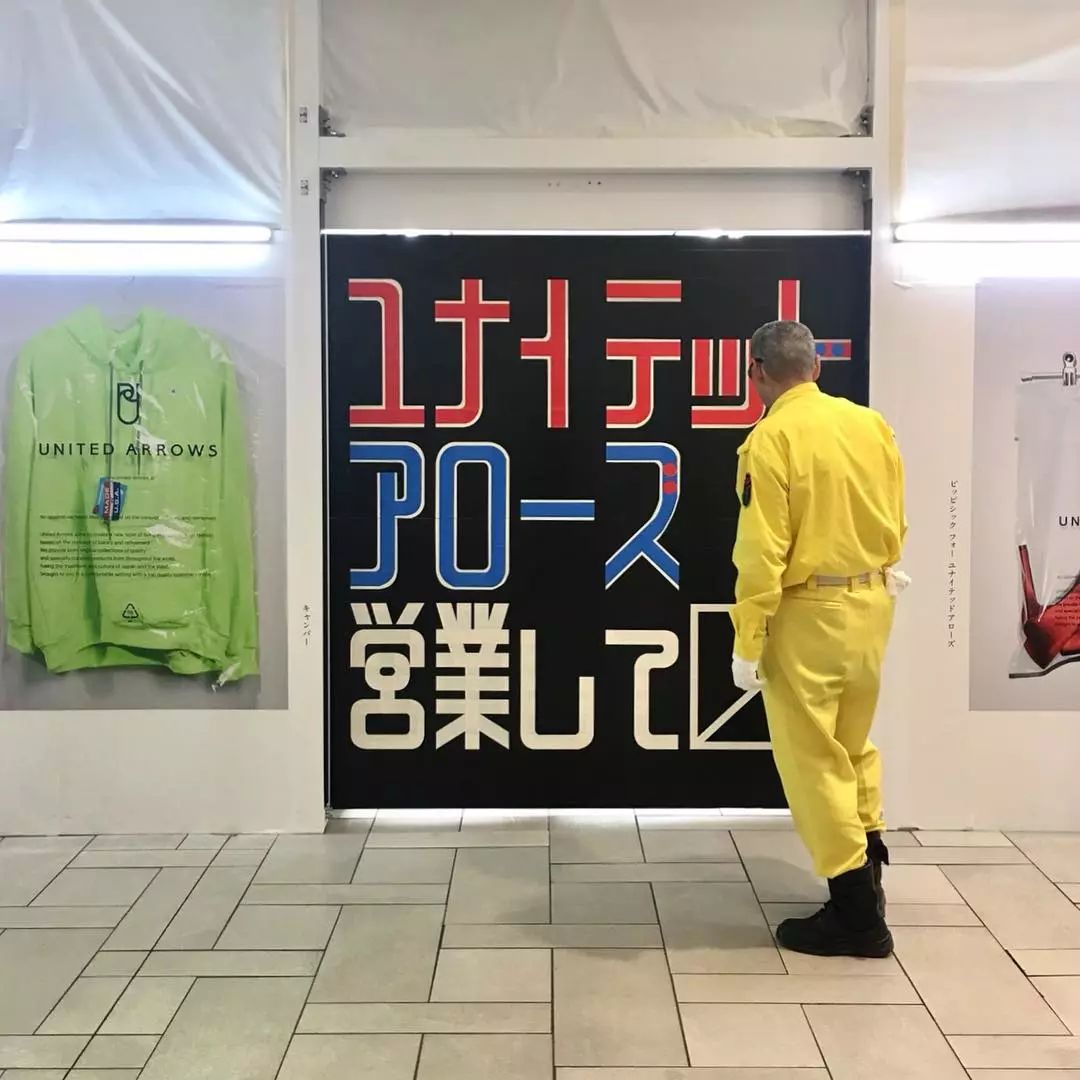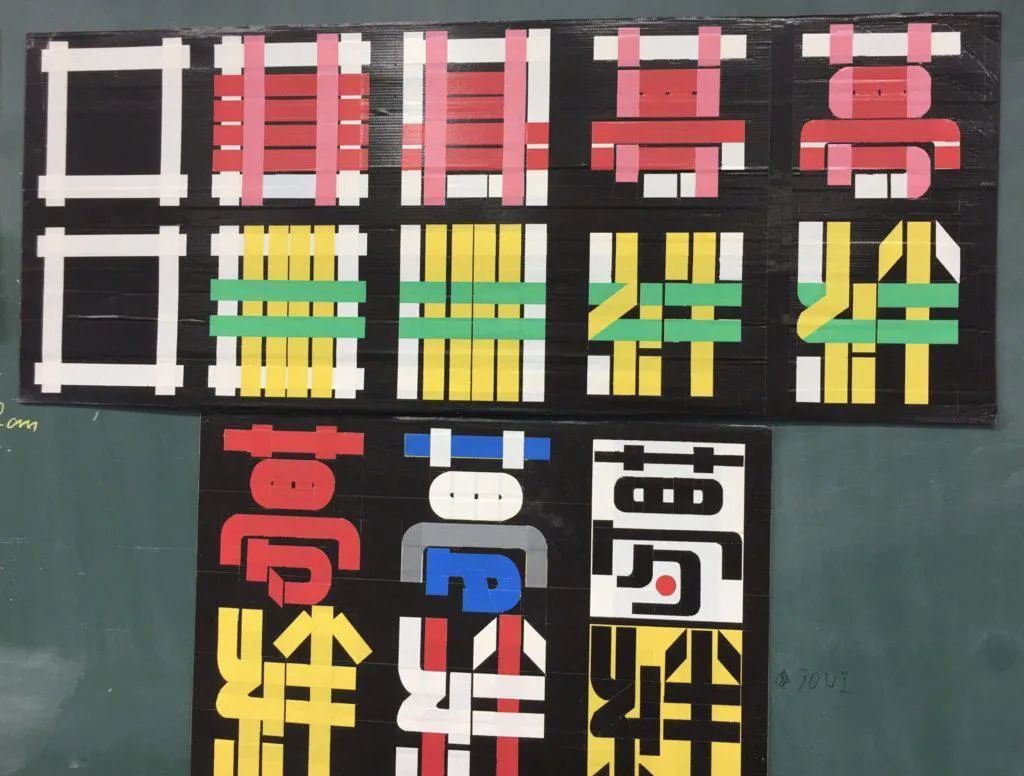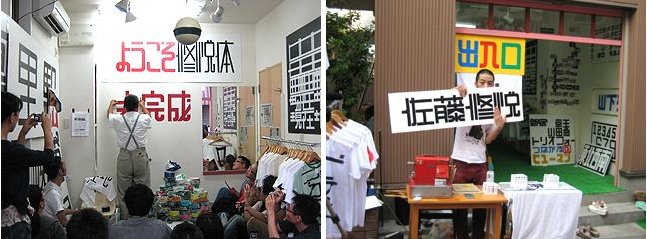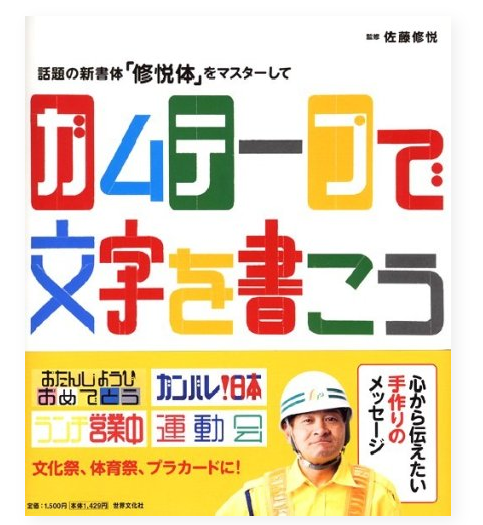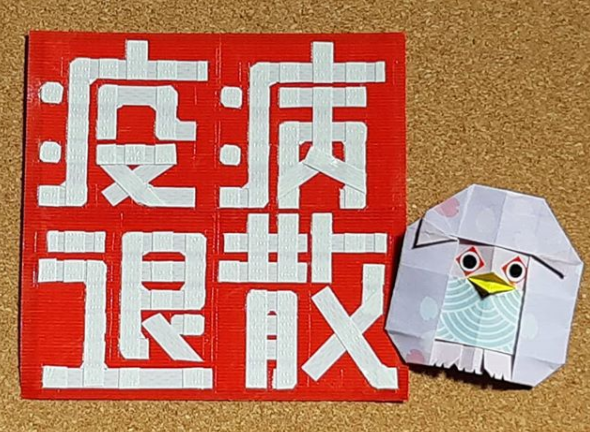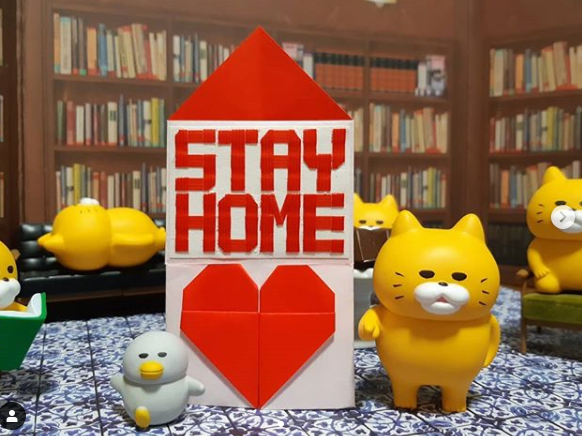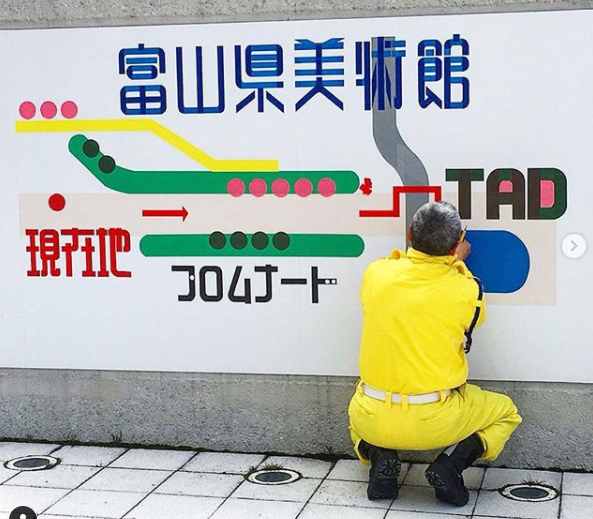
这位保安大叔,竟用胶带搞“设计”?
最近看到一个视频
开始以为是个青铜
看到最后才发现是个王者
这位大叔来自日本
职业是地铁站的安全防护和交通疏导
一个偶然的机会
他开始用胶带制作地铁站内的标语
没想到却火遍了全网络
有无数网友特地去地铁站内
找寻他的字体作品
在朋友圈打卡、合照
更是有心人将他的字体整理搜集起来
命名为“修悦体”
大家都称他为最接地气的字体设计师
他就是笑起来超可爱的佐藤修悦
01
67岁地铁站保安
用胶带搞“设计”
有去过日本东京
坐过地铁的小伙伴一定知道
日本地铁线路错综复杂
车站内各种入口、换乘
简直让人晕头转向
而佐藤修悦的工作就是在东京
交通最繁华的地段新宿车站内
1953年出生的佐藤
最早是在银行上班
之后做过报纸的排版工作
又来到了车站担任警备员
可以说他这辈子都在
社会最基础的岗位上兢兢业业
2003年新宿站内进行地下通道改建
佐藤在站内负责引导乘客
由于施工的原因,车站内混乱如同迷宫
很多乘客根本找不到想要去的出入口
每天从早到晚,佐藤可能需要回答上百次
同样的指路问题
于是,他就想是否可以制作标识
来引导大家方向,快速找到目的地
(你现在所看到的这些字体引导牌
都不是通过电脑打印出来的
而是佐藤纯手工制作
用胶带贴出来的哦!)
佐藤便尝试用胶带来做导示牌
这样既不浪费资源,不用专门去打印
字体效果也十分醒目
最重要的是,若是被领导责问起
因为是胶带制作,还可以快速去除
说干就干,佐藤便用施工现场的
白色、黑色和黄色的布基胶带开始制作
没想到效果意外的好
大大减轻了日常询问工作
于是车站便没有过多的干涉
而是让佐藤继续做下去
由于在高中学过一些字体课程
和在报社的排版经历
让佐藤在做字体时游刃有余
颜色上也从最开始的白、黄、黑色
慢慢的被批准使用红色、蓝色和绿色
并且与列车的颜色相匹配
仔细观察佐藤的胶带字体
你会发现这些字
不是用胶带横平竖直的拼好就好
而是在细节处增加了很多圆角的设计
这其实是他的刻意之为
佐藤会用刻刀在贴好的字上
进行二次加工,使字的外框变圆
佐藤对此有自己的理解:
将字体故意设计成圆角
其实是为了减轻了用户
在不熟悉的空间中的陌生感
柔和的外观会让人们感觉更亲切
佐藤从来没有经历过专业的美学教育
但是他却创造了属于他的胶带字体时代
不得不说这其中,除了他对生活的观察
更少不了那份对职业的热爱
和他天赋异禀的艺术感知力
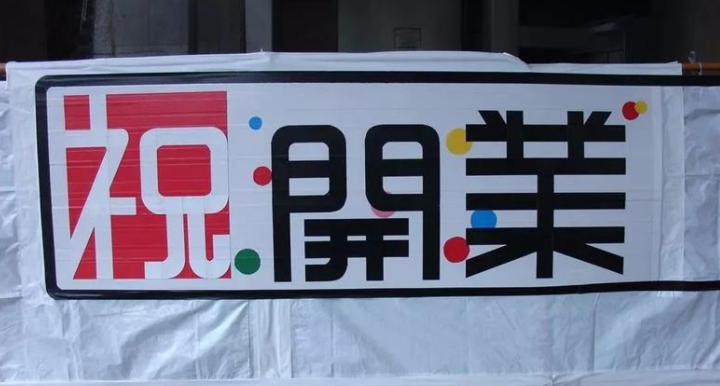
02
胶带字到底是如何做成的?
一起来看看,这些用胶带字
到底是如何贴出来的吧!
首先当然要准备好基础工具
胶带、量尺、剪刀和美工刀
开始我以为佐藤
是按照笔画来拼贴字的
直到我看了制作视频
才发现自己图样图森破
“梦”、“绊”字的制作顺序
话说最上面两行,前1.2.3.的步骤你看明白了么
确定好“画纸”后
先上下粘两个横条
像是两条辅助线
并在上面用尺子平均划分格子
避免一会贴字,大小不一
横向确定好之后
开始依次贴竖条
是不是感觉一头雾水
完全看不懂在干什么
别着急,我们继续往下看
佐藤用美工刀去除四周多余的胶带
(其实在这一步
文字的笔画部分已经贴完了
只是我们还看不懂而已)
为了让文字能够更好的辨识
字与字之间要留出空隙
只见佐藤咔咔咔撕掉多余的胶带
突然间好像就豁然开朗了
几个无厘头的方块
瞬间变成了一段文字
你以为这就结束了?
佐藤又进行了一次细化
在字的边角处呈现圆形的弧度
加强设计感
日本两个字用了红色和蓝色
胶带重叠贴合
让字看起来更丰富、立体
左边的片假名「ガンバレ」的处理
用圆圈来代替其余的笔画
加油!日本
看完你如何感想
象君是实在佩服佐藤
对于文字笔画和空间思维的掌控
我作为个美术生都甘拜下风
明明看起来很简单
但实际没两下真功夫,根本做不来
03
大叔走红后的生活
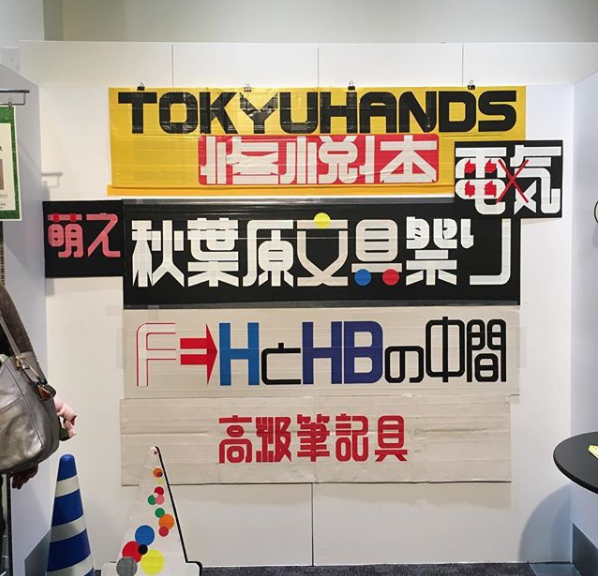
其实早在10多年前
就有电视、报纸对佐藤进行采访了
当时还办过一场小型的展览
在现场演示如何制作
2009年的时候还专门出了一本书
教大家如何用胶带来“写字”
Instagram上还有网友跟着书本
模仿他的胶带字体呢
最近几年,佐藤的作品还参见了不少展览
去年在富山县美术馆
馆方还特地邀请他来现场
在墙面制作美术馆的导向图
这是它为美术馆设计的字体
展览现场的作品一赏
佐藤设计的自己名字
无论是颜色搭配,还是字体样式
都让人很难想象
这是一位自学成才的保安大叔作品
水平堪比专业设计师!
在美术馆现场演讲制作心得
美术馆还将佐藤的作品
印成了明信片周边
在今年年初
佐藤还为《私たちの S.W.展》
(一个潮流艺术家展览)
设计了主视觉的logo标识
看来佐藤的设计
深受当代年轻人的喜爱!
另外今年的文具大赏的logo
也是佐藤做的哟!
是不是觉得特别的眼熟
之前看到还以为是某个字体
现在才恍然大悟!
佐藤在现场用胶带
制作的背景板
胶带本身就是文具的一类
这样一想,文具厂商
找佐藤来做设计
简直太适合不过了!
佐藤虽然已经67岁了
但他的创作却被无数年轻人喜爱
现在人人都有手机
佐藤的作品被很多网友发到了网上
甚至在地铁站内
许多人专程前来打卡合照
新宿站内
▽
United Arrows横滨商店
▽
每当他们发现了新的修悦体标志
还会发布在instagram上
现在#修悦体#的tag下
已经有了数千张照片
新宿站东口吸烟区
▽
以佐藤作品的受欢迎程度
现在的他可以说是一名
不折不扣的“网红”咯~
不过他也并没有因为走红
辞掉地铁站的工作
而是仍在岗位上恪尽职守
如果你在东京生活
或以后会去东京游玩
有空记得去新宿地铁站瞅瞅
说不定就会看到佐藤制作的标识哦!
7月24日网友新宿站打卡